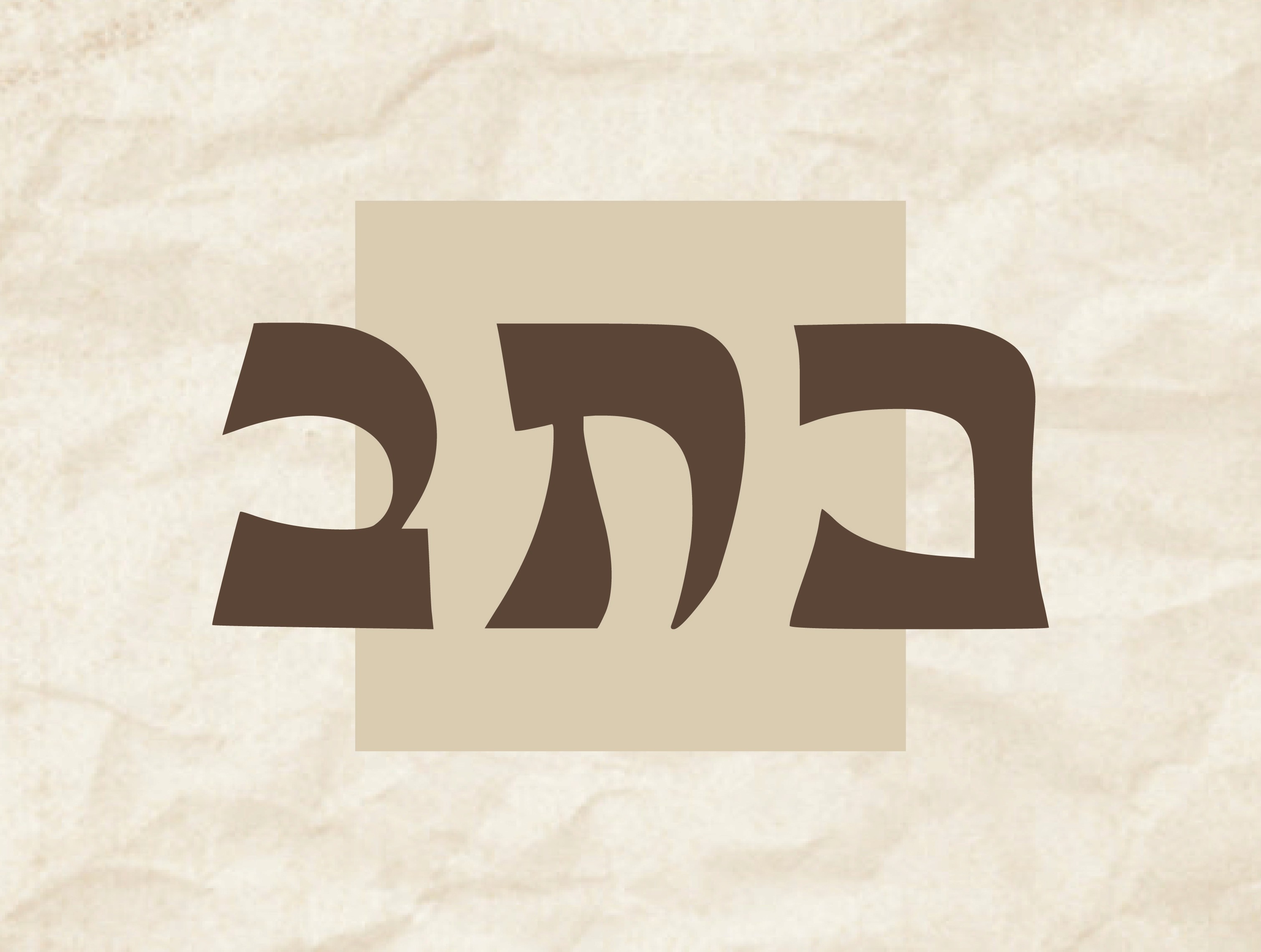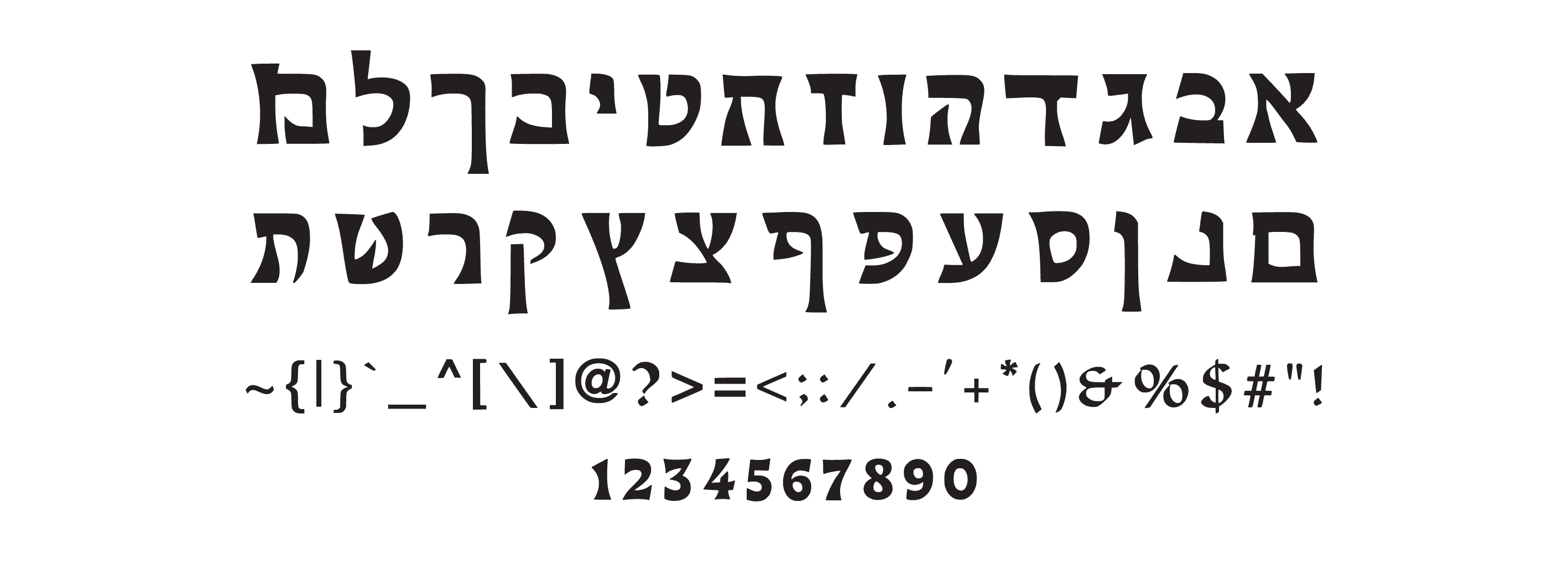
פונט כתב
פונט עברי עבה ובולט בסגנון רטרו-אותנטי, מושלם לכותרות ולוגואים עם נוכחות.
כתב — הפונט שלא נשאר ברקע
יש פונטים שמספרים סיפור רק בלחישה, ויש כאלה שצועקים אותו בגאווה.
כתב הוא פונט עם נוכחות חזקה שלא מבקש רשות — הוא פשוט נכנס ומכתיב את הקצב.
הוא מזכיר שלטי עץ עתיקים וכתבי יד מהימים של פעם, עם קווים עבים, מלאי עוצמה, אך גם עם מגע רך שמזכיר עבודת יד.
הפונט הזה מתאים לכל עיצוב שרוצה להרגיש שורשי, אותנטי, כזה שמספר סיפור של מסורת.
✶ כותרות מרשימות ומודגשות
✶ עיצובי נוסטלגיה, רטרו ומורשת
✶ לוגואים אותנטיים
✶ פוסטרים עם ניחוח של פעם